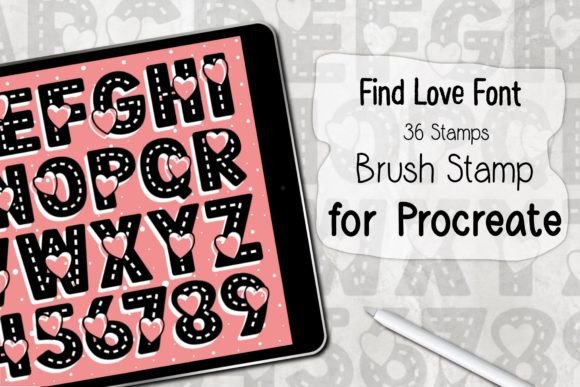
Find Love Font Procreate Brush Stamp
Поиск подходящих элементов дизайна может быть сложным, но Find Love Font Procreate Brush Stamp предлагает исключительную коллекцию, которая мгновенно улучшит вашу работу.